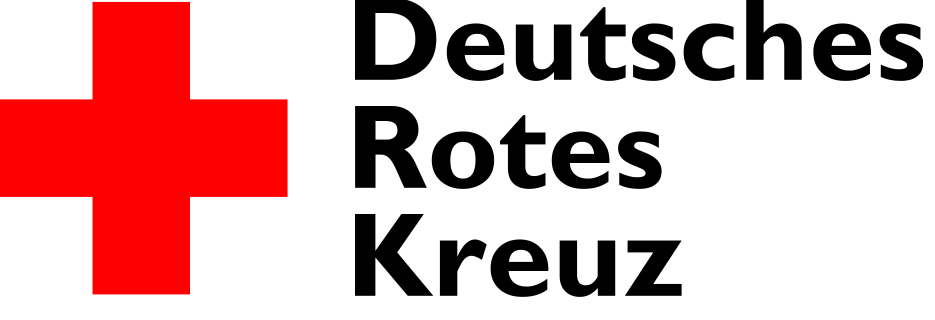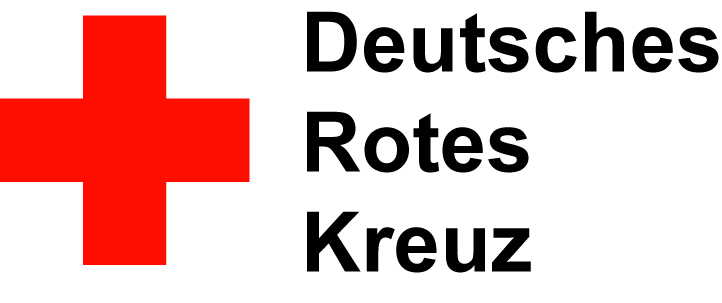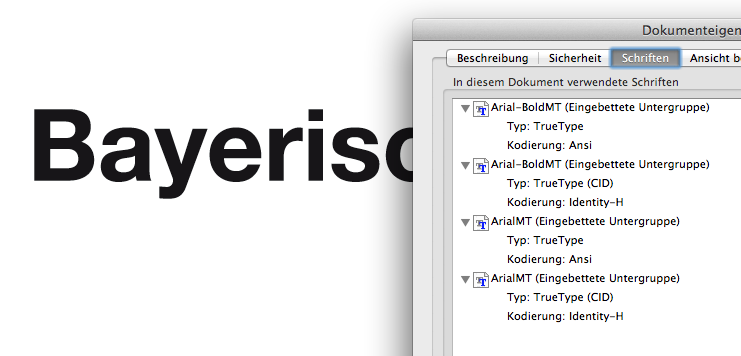
Suche Schriftart vom Logo des Bayerischen Roten Kreuzes
kennt jemand die Schriftart vom Logo des Bayerischen Roten Kreuzes?
Ich habe schon im Internet gelesen, dass es die "Gill Sans Bold" sein soll, aber das stimmt nicht...
Da hat wohl irgendwer beim Erstellen des Wikipedia-Logos ein anderes Landes-Rotes-Kreuz auf das Bayrische umgebaut, und sich dabei in der Schriftart vergriffen.
Ich habe mich mal durch die Google-Bildersuche gewühlt, und da auch ein Gill Sans Logo gefunden:
An die Gill Sans kann ich mich noch gut erinnern – aber das muss rund 30 Jahre her sein. Jetzt sieht es eher so aus.
(Das DRK heißt [als quasi Ortsverband] nur in Bayern BRK, ansonsten sollte sich da aber CI-mäßig nichts unterscheiden.)
Das BRK verwendet die HelveticaNeue, auch im Logo, wie ein paar aktuelle pdfs verraten. Das wikipedia-Logo dient wohl nur der groben Orientierung.
Das Wikipedia-Logo stammt ja nicht vom BRK, sondern wurde von einem Wikipedia-Mitglied erstellt:
Und dieser hat wahrscheinlich ein DRK-Logo umgearbeitet. und wenn schon, wie wir aus dem Polizei-Fraktur-Strang wissen, dass Frakturschriften, die nur verschnörkelt sind, schon nicht unterscheidbar sind, wie bitteschön soll da ein normaler Krankenpfleger  Arial und Helvetica unterscheiden können?
Jetzt habe ich Gewissheit über die aktuell zu verwendeten Schriftarten beim Deutschen Roten Kreuz.
Ich Handbuch steht:
Verwendet werden ausschließlich die Schnitte:
HelveticaNeue LT 55 Regular bzw. Roman
HelveticaNeue LT 75 Bold
HelveticaNeue LT 56 Italic
Die Standard-Schriftgröße beträgt 10 Punkt.